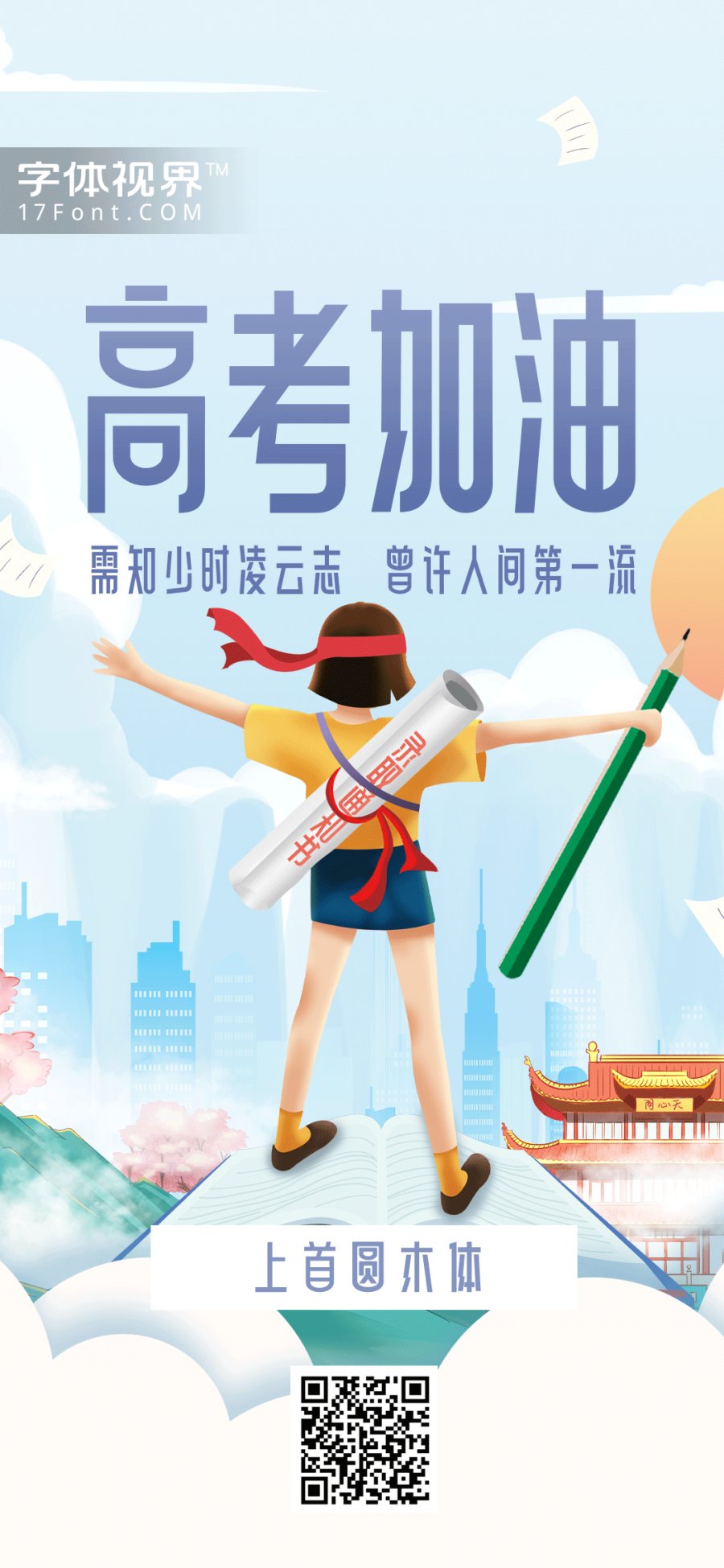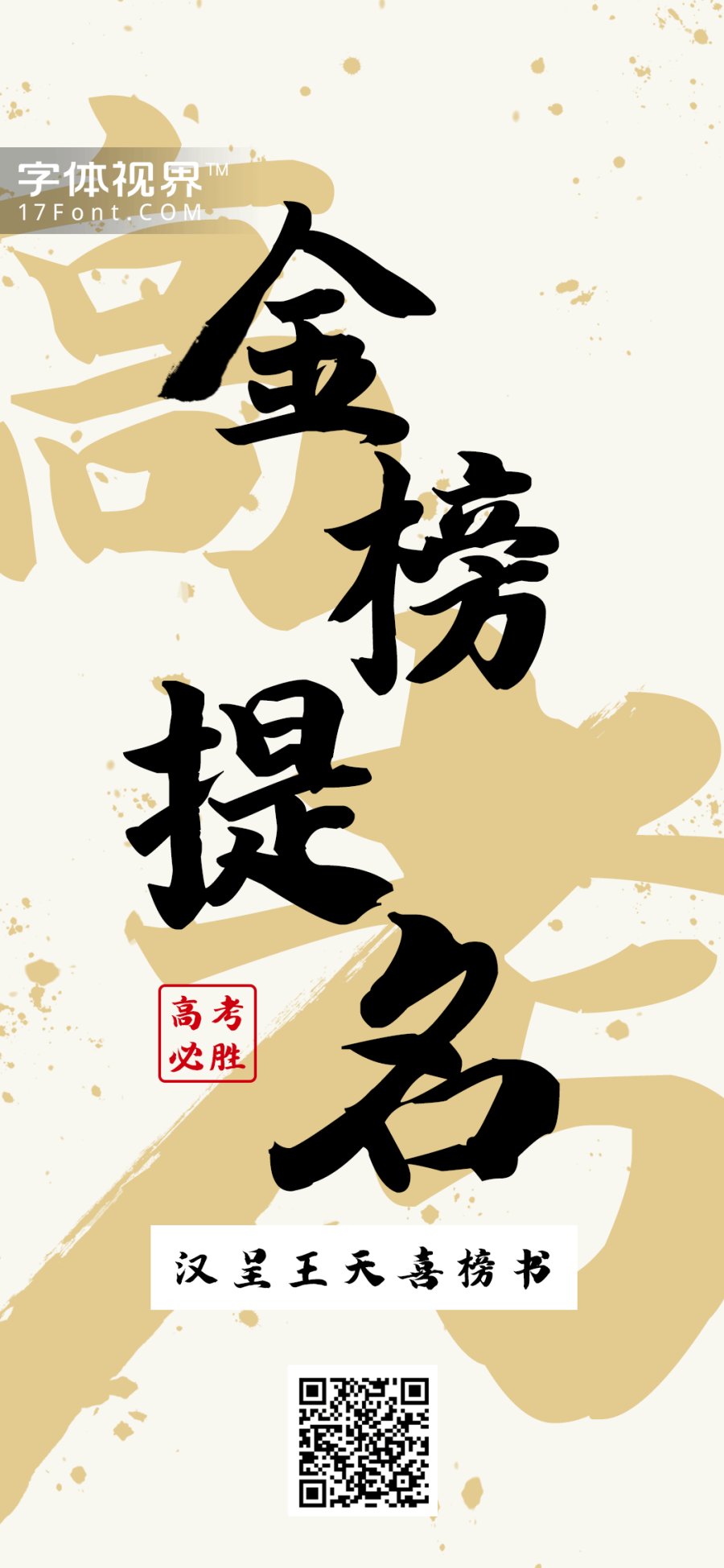
以梦为马,奔赴考场,高考加油
愿披星戴月走过的路,
终将会遍地繁华,
上首圆木体具有一种气贯长虹的神采,
断开的部分打破原有的结构空间,
提高了层次感和灵活性。
上首圆木体
愿你合上笔盖的那一刻,
有着战士收刀入鞘般的骄傲!
嗷呜嗷呜给你糖字形圆润可爱,
提醒各位考生要注意书写规整,
字可以写得不漂亮,但一定要字迹清晰哦。
嗷呜嗷呜给你糖
祝愿每一位高考生:
自信登场,全力以赴!
落笔生花,圆梦今夏!
汉呈王天喜榜书字体祝愿每一位考生金榜题名
汉呈王天喜榜书字体